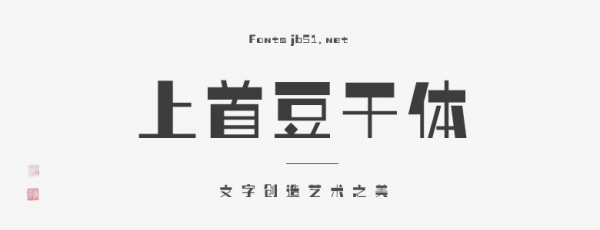
上首豆干體,簡(jiǎn)體中文約6763字,字體風(fēng)格穩(wěn)重呈方塊形,整體特征堅(jiān)硬、有力。具有現(xiàn)代、國(guó)際化的指向性字形緊湊,但不失美感。剛正而不失穩(wěn)重,字體字型粗細(xì)不一,非常有意思,具有很好的視覺(jué)感,適合于文化類(lèi)的宣傳設(shè)計(jì)、商業(yè)類(lèi)品牌的廣告和產(chǎn)品包裝設(shè)計(jì)以及個(gè)性化文字排版等較多場(chǎng)景。